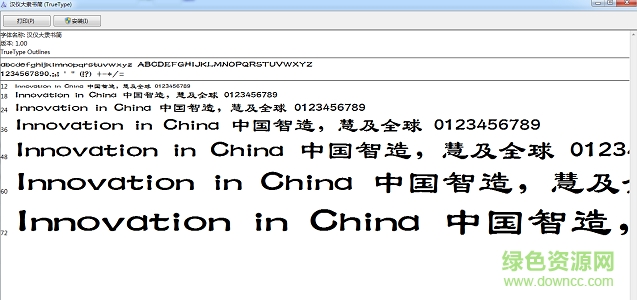
hyf1gj是什么字體?hyf1gj字體是漢儀大隸書簡的官方字體代碼,結(jié)構(gòu)規(guī)范,典雅莊重,極具美學(xué)價值,常常用于藝術(shù)設(shè)計(jì)方面,需要這款字體的朋友趕緊來綠色資源網(wǎng)下載吧!
隸書,有秦隸、漢隸等,一般認(rèn)為由篆書發(fā)展而來,字形多呈寬扁,橫畫長而豎畫短,講究“蠶頭雁尾”、“一波三折”。根據(jù)出土簡牘,隸書起源于戰(zhàn)國。